Style desain modern yang sederhana dan bersih, untuk menciptakan desain yang canggih serta profesional. Gaya desain yang canggih tersusun dari font dan warna yang tampil sederhana dan elegan. Kombinasi font dan warna pada desain logo teknologi akan dipilih yang menciptakan kesan canggih dan modern.
Gaya desain yang modern akan memiliki ciri bersih, kaku dan tebal, seringkali menggunakan efek tiga dimensi dan efek nyata. Desain juga memiliki style minimalis dengan jumlah kombinasi warna dan tipografi terbatas. Kombinasi warna dan font perlu menyesuaikan jenis brand teknologi agar relevan dan menarik.
DESAIN BRAND TEKNOLOGI
Brand teknologi dalam berbagai bidang bisnis secara umum seringkali memiliki style yang sederhana. Dalam desain logo dan desain branding baik warna dan font akan tampil minimalis. Untuk menciptakan desain brand teknologi yang relevan, gunakan kombinasi font dan warna seperti:
Tipografi Tajam, Tebal dan Sederhana
Branding teknologi sering menggunakan font yang tebal, tajam dan kaku sehingga menciptakan kesan kuat dan profesional. Font tebal akan menciptakan kesan brand teknologi yang kuat dan handal. Bentuk huruf yang tajam akan relevan menciptakan kesan desain yang canggih.
Warna Netral, Gelap dan Neon
Untuk warna yang relevan dengan desain brand teknologi, biasanya menggunakan warna seperti netral, gelap dan neon. Penggunaan warna netral seperti hitam dan putih akan berguna menciptakan kontras dan keseimbangan visual. Sementara itu kombinasi warna gelap dan neon sering digunakan untuk menciptakan kesan canggih dan futuristik.
Efek Visual 3D dan Texture
Desain teknologi sering pula menggunakan efek visual seperti 3D dan tekstur agar lebih berdimensi. Penggunaan efek visual dalam desain grafis bertema teknologi akan menciptakan kesan yang canggih. Ini juga relevan merepresentasikan teknologi futuristik masa depan.
Efek Gradasi Warna
Tidak hanya menggunakan warna neon, brand teknologi sering juga menggunakan warna gradasi agar lebih menarik. Efek warna gradasi akan menciptakan desain yang tampak halus dan memiliki kesan dinamis. Warna gradasi bisa menciptakan efek 3D sehingga efektif merepresentasikan desain brand teknologi.
Jenis Logo Geometris
Pada desain logo teknologi, jenis logo yang cocok adalah style logo geometris baik yang inisial maupun wordmark. Bentuk geometris yang sederhana dan bersih akan menciptakan kesan profesional dan handal. Tipografi dan ikon berbentuk geometris banyak ditemui pada logo teknologi untuk tampil canggih dan handal.
KOMBINASI FONT LOGO TEKNOLOGI
Brand teknologi memang paling sering menggunakan gaya font tebal dan tajam, namun utamanya garis font harus berbentuk sederhana. Untuk menciptakan kontras bisa menggunakan ketebalan berbeda dan gaya huruf yang beda. Kombinasi font sederhana dan warna gelap serta neon mencolok yang akan sesuai dengan brand teknologi.
Font Gaming & Esports
Untuk desain brand gaming atau e-sport penggunaan font yang cocok memiliki gaya huruf yang geometris dan sederhana. Gaga font geometris seperti Orbitron akan memiliki gaya huruf geometris seperti persegi dan sederhana.
- Headline Orbitron
- Sub Judul Radjani
- Paragraf Exo 2
Font Orbitron yang memiliki style geometris dapat menciptakan kesan canggih sehingga digunakan sebagai font utama atau headline. Sementara itu font Radjani juga bisa memiliki gaya huruf geometris tetapi lebih sederhana sehingga mudah dibaca pada ukuran kecil. Gaya font yang lebih sederhana akan digunakan sebagai font sub judul dan paragraf.
Font Brand Crypto & NFT
Untuk desain brand crypto dan nft penggunaan font geometris sederhana juga akan relevan. Kombinasikan font geometris sederhana dengan variasi gaya huruf berbeda untuk menciptakan kontras.
- Headline Aldrich
- Sub Judul Michroma
- Paragraf Kanit
Font aldrich yang digunakan sebagai font headline memiliki huruf lebih tebal sehingga akan lebih menonjol. Sementara font geometris pada sub judul tampil lebih tipis, dan teks paragraf menggunakan font yang tidak begitu kaku. Kombinasi gaya font geometris akan menciptakan desain brand crypto yang handal dan profesional.
Font Brand Startup
Branding startup juga kebanyakan menggunakan style desain untuk teknologi agar tampak canggih dan handal. Penggunaan font geometris akan mempresentasikan brand startup yang profesional. Biasanya akan menggunakan style logo sederhana sehingga menggunakan font geometris yang bersih.
- Headline Radjani
- Sub Judul Oxanium
- Paragraf Fira Code
Style font Radjani tersebut memiliki huruf yang sederhana sehingga akan mudah terbaca sebagai font utama. Gunakan font Oxanium yang juga bergaya geometris untuk sub judul agar kombinasi font harmonis. Sementara font monospace yang cocok merepresentasikan brand teknologi canggih, digunakan sebagai body text.
Font Brand Fintech Digital Banking
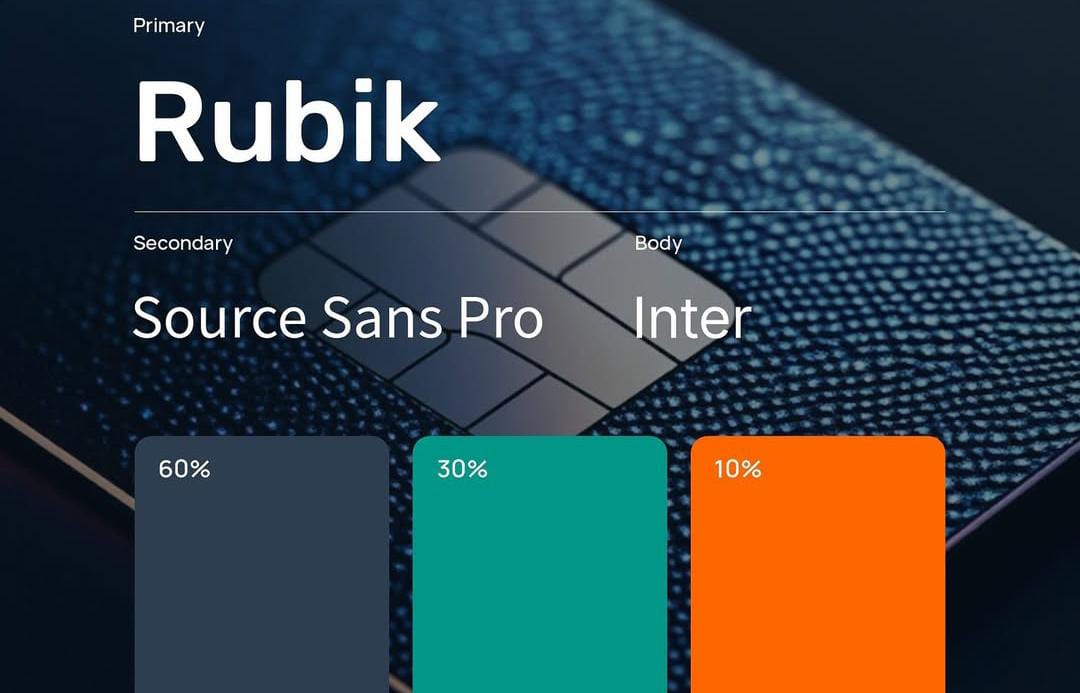
Untuk branding dalam bidang keuangan atau digital Banking akan relevan pula menggunakan font geometris. Penggunaan font geometris sederhana akan menciptakan desain brand keuangan yang handal dan terpercaya. Perbedaan ketebalan dan gaya huruf akan menciptakan kontras meski menggunakan jenis font yang sama.
Desain brand teknologi banyak menggunakan kombinasi warna dan font yang merepresentasikan kesan canggih dan profesional. Gaya font geometris akan tampil kaku, tajam dan tebal sehingga berkesan profesional. Sementara itu kombinasi warna untuk brand teknologi sering menggunakan warna gelap dan neon. Kombinasi gaya font dan warna neon akan merepresentasikan jenis brand teknologi yang canggih dengan baik.